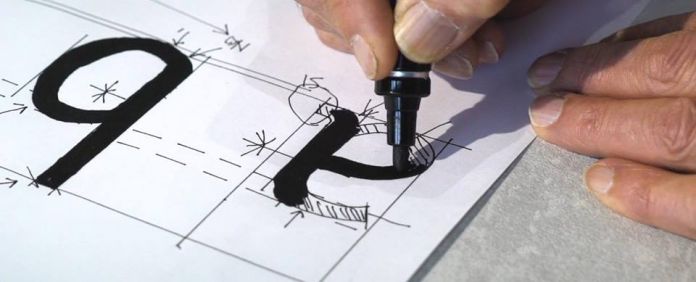
Il primo font per dislessici: EASYREADING
Il compito del design è quello di semplificare le nostre vite ed è proprio questo l’obiettivo portato a termine da Federico Alfonsetti e il suo team: creare un font che avesse come target di riferimento la popolazione dislessica, ma che allo stesso tempo fosse chiaro e comprensibile per tutti.
La dislessia è un disturbo neurologico che ci rende incapaci di leggere e comprendere un testo pur riuscendone a riconoscere le singole parole o lettere ed è più diffuso di quel che si pensa, visto che ne soffre il 10% della popolazione mondiale.
Da questa necessità nasce EASYREADING, il primo font per dislessici dalla progettualità così discreta da risultare impercettibile agli occhi di un lettore classico.
Il font conta 811 glifi ed è capace di agevolare sia il lettore dislessico che il lettore comune, che con ogni probabilità non si renderà conto di trovarsi di fronte a un carattere “speciale”.
“Nella decifrazione delle lettere un dislessico incontra due grandi difficoltà di natura pratica, escludendo per un momento le implicazioni di natura psicologica. La prima è l’effetto affollamento della pagina scritta, con troppi segni e poco spazio, la seconda riguarda la possibilità di confondere tra loro lettere simili nella forma, come per esempio la d, la b, la p e la q minuscole, che nel normale design dei caratteri divergono soltanto per l’orientamento. Per questo abbiamo disegnato lettere con grazie più allungate, creando spaziature più ampie e un maggior respiro di lettura, e abbiamo fatto uno sforzo particolare per differenziare le lettere a livello formale. In questo modo il lettore può impegnare le energie risparmiate nella decifrazione delle lettere nella comprensione del testo”.
Oltre all’editoria  e altri settori in cui la leggibilità è una questione di vitale importanza,  il font, disponibile dall’inizio del 2018 in una nuova versione Extended che comprenderà anche i caratteri degli alfabeti greco e cirillico, può trovare un importante ambito di utilizzo anche nella comunicazione dei musei, come già accaduto in occasione della mostra allestita a Milano lo scorso inverno per festeggiare i 90 anni di Arnaldo Pomodoro, Dove tutti i supporti di comunicazione, dai totem alle didascalie delle opere fino alla cartella stampa, sono stati realizzati con il font EASYREADING.
“Fare attenzione alla leggibilità per tutti è un modo per riportare il contenuto al centro, evitando di rincorrere inutili virtuosismi”, ricorda il “papà” di EasyReading. Una lezione munariana, oltre che un tentativo di coinvolgere il 10% della popolazione che soffre di dislessia nella fruizione della cultura.